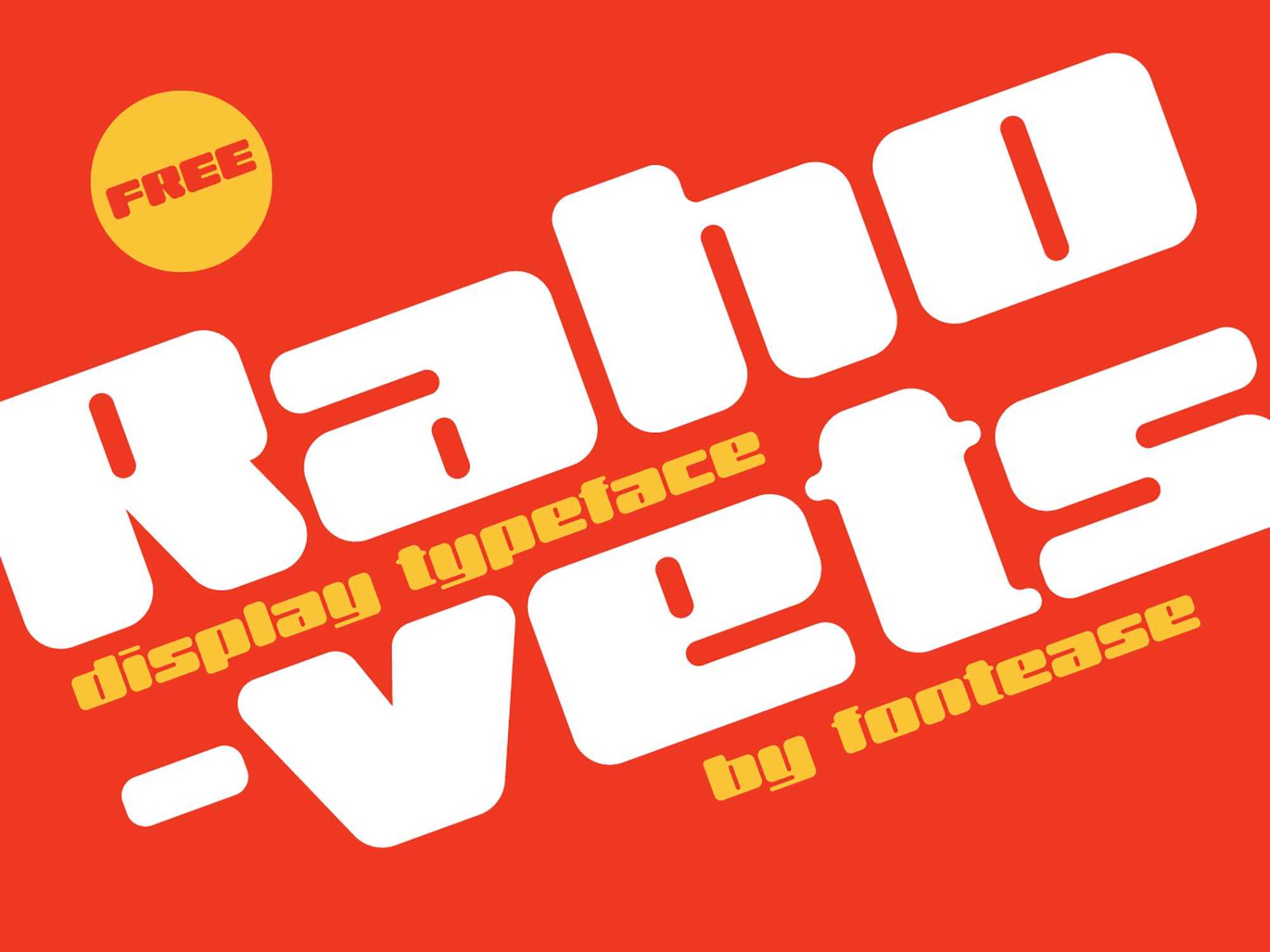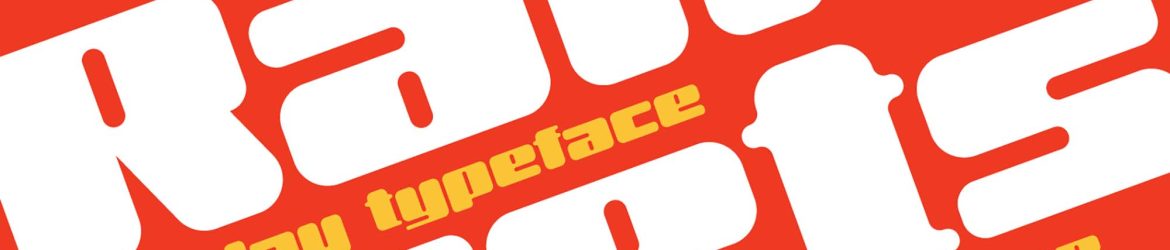
A fonte ‘Rahovets Retro Display’ é uma criação única que traz um toque vintage e moderno à sua arte. Ela combina elementos de estilo retro com uma paleta vibrante e contrastante, criando um efeito que destaca-se em qualquer design. Seja em letras grandes para headlines ou em linhas sutis para subtítulos, essa fonte oferece uma aparência inegável e inconfundível. É perfeita para aquelas criações que buscam um visual chamativo e memorável, capaz de destacar sua arte em qualquer formato. Este recurso gráfico se torna o centro das atenções, garantindo que sua marca ou arte seja lembrada. Não espere para incluir ‘Rahovets Retro Display’ em seu próximo projeto.
Licença: , a retro display font available for free for personal and commercial use. Not every font has an interesting origin, but this one is inspired by and named after an inscription on the most popular Bulgarian compact oven from the communist era. It supports Latin and Cyrillic languages and brings you a selection of characters where even the smallest of details like the thin tittles of its letters can be noticed. Although it’s a retro font, its usage in today’s projects is what will allow its thick strokes and small apertures to stand out when used both online and in print.